7 font các chuyên gia thiết kế hay dùng
1. Helvetica
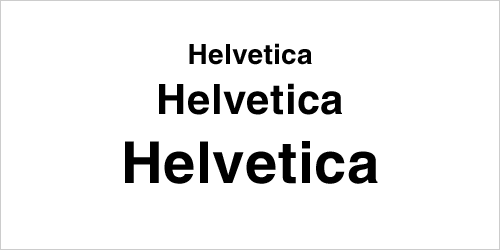
Helvetica font
Helvetica là font hay được các chuyên gia thiết kế(và cả những người nghiệp dư) hay sử dụng nhất. Mặc dù Helvetica nhận được rất nhiều khen ngợi, có một số người vẫn phàn nàn về khoảng cách giữa các chữ quá gần nhau.
2. Trajan
Trajan
Font Trajan hay được sử dụng trong các poster của Hollywood, bạn có thể xem các poster dùng font Trajan tại đây: Click here.
3. Garamond
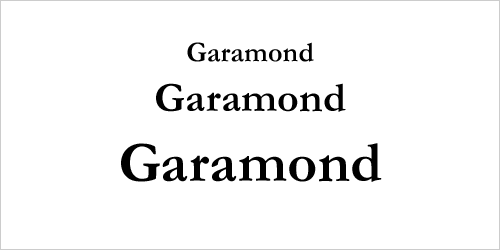
Garamond
Có rất nhiều phiên bản của Garamond, trong đó, Adobe Garamond hay được sử dụng nhất. Garamond được ưa thích sử dụng trong báo chí, sách, website và các đoạn text dài.
4. Futura
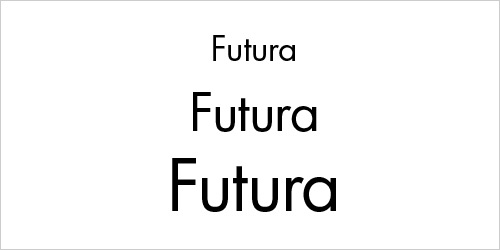
Futura
Futura hay được sử dụng trong logo, các quyển sách dùng chữ cỡ nhỏ. Futura tượng trưng cho tính hiệu quả và phát triển.
4. Bodoni
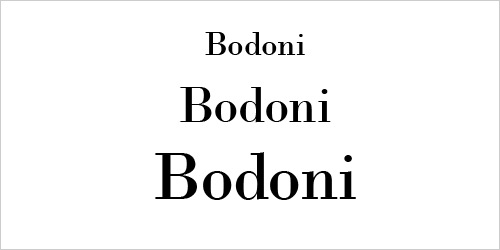
Bodoni
Bodoni là font hay được sử dụng trong tiêu đề, text để trang trí, logo. Nhìn chung, Bodoni có là font có tính thẩm mỹ cao.
6. Bickham Script Pro
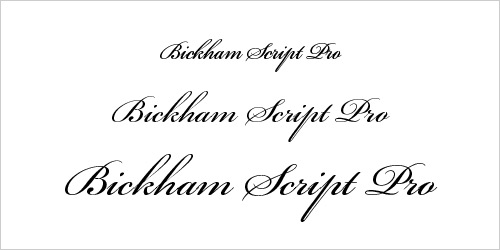
Bickham script pro
Bickham Script Pro hay được sử dụng trong những việc mang tính trang trọng.
7. Frutiger
Fruitiger
Font Frutiger được thiết kế khiến chúng ta có thể dễ dàng nhận ra từng con chữ trong từ. Vì thế nó hay được sử dụng trong báo chí, và trong các logo của Web 2.0.